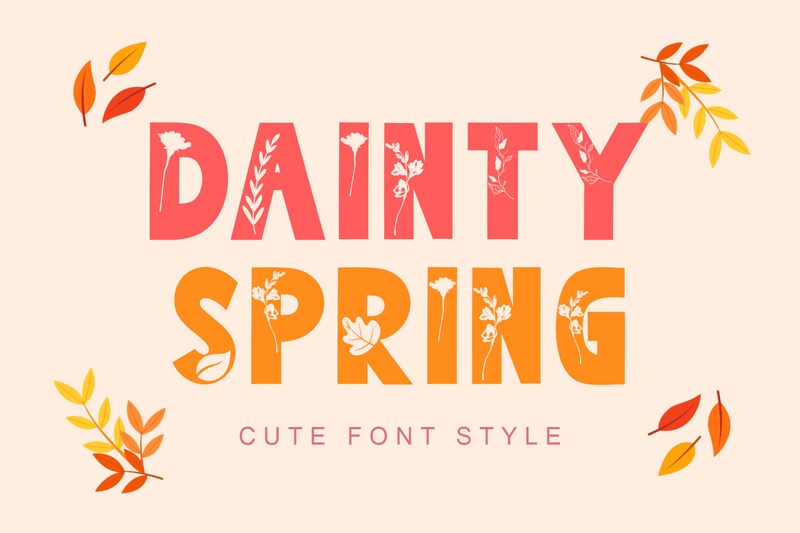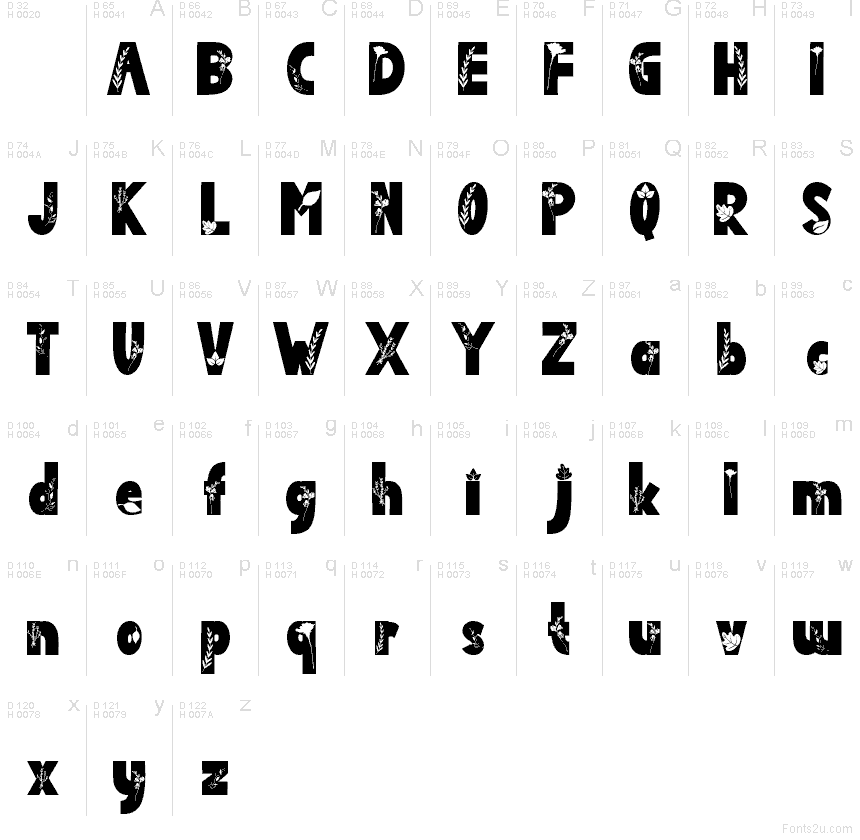
Dainty Spring od Yoga Letter je dekorativní font typu display se zaoblenými tvary písmen a jemnými květinovými detaily. Zakomponované větvičky, lístky a drobné květy mu dodávají pocit ručně zdobené zahrady, aniž by přitom ztratil svou pevnou a jasnou strukturu.
Dainty Spring skvěle funguje u jarních pozvánek, log květinářství, obalů butikových značek, scrapbookových titulků nebo sezónních plakátů, protože dekorativní prvky samy o sobě nesou dané téma. Hodí se také na přáníčka, etikety a nadpisy, které vyžadují rostlinný motiv namísto obyčejného písma.
Dainty Spring